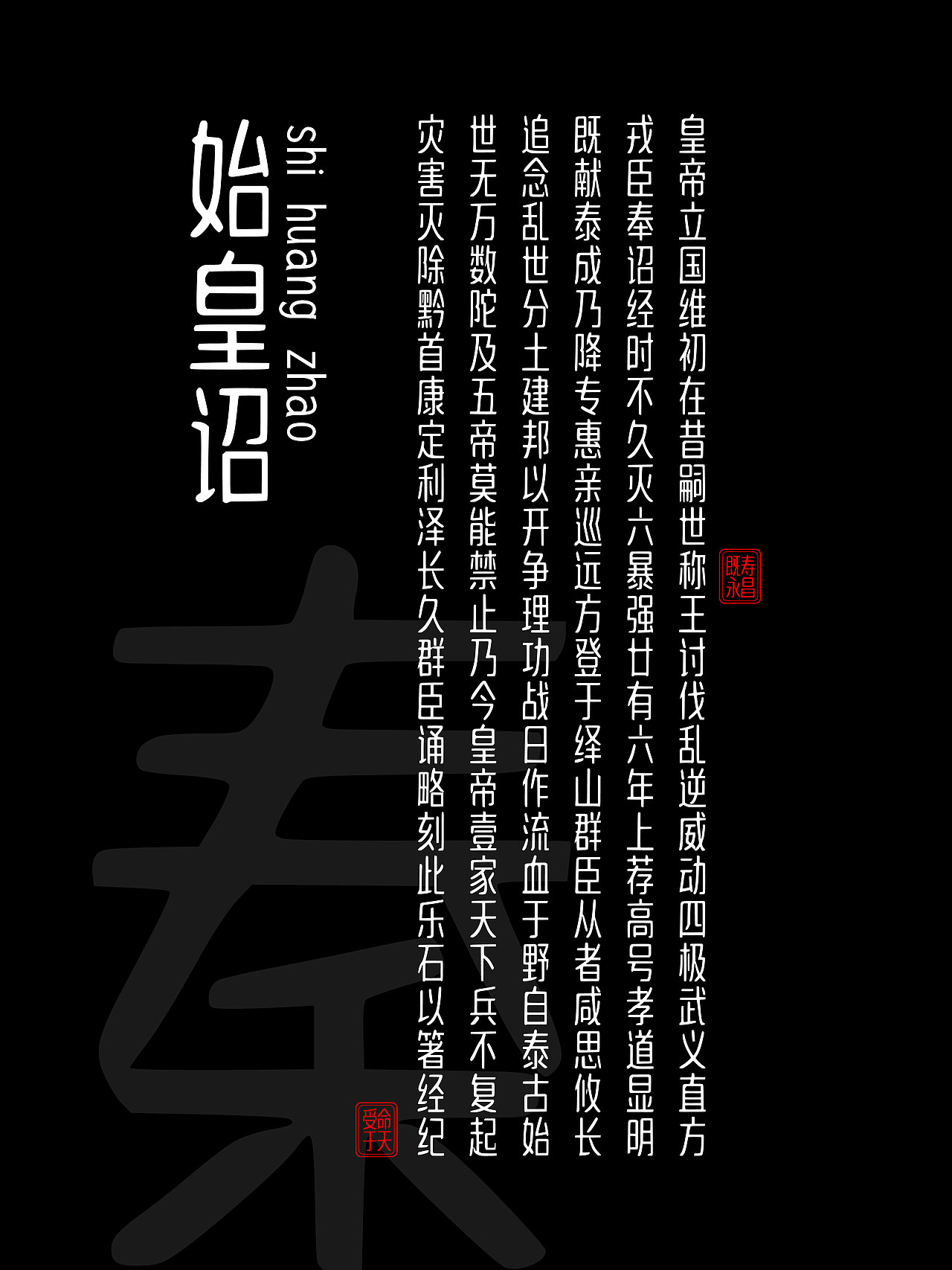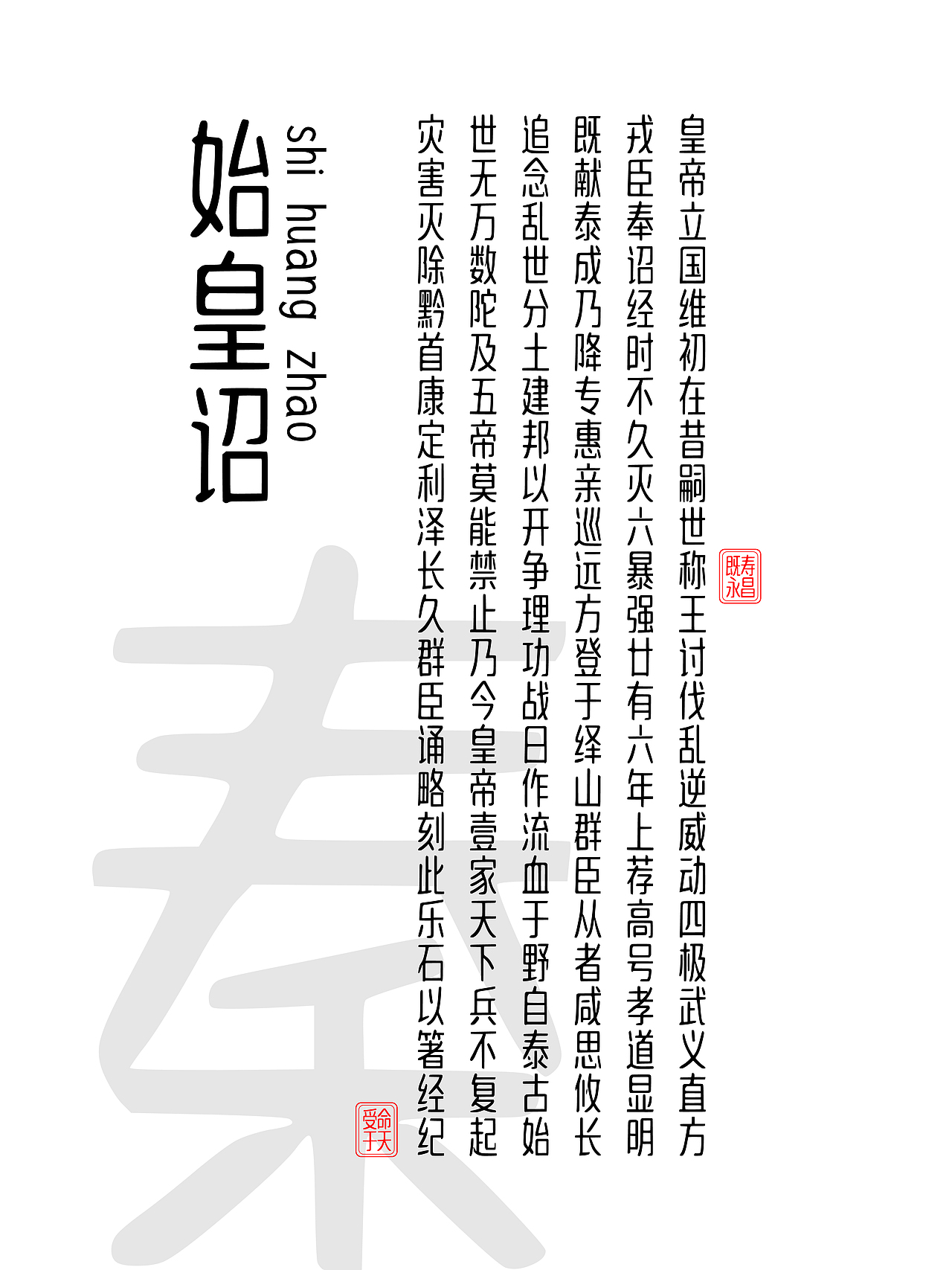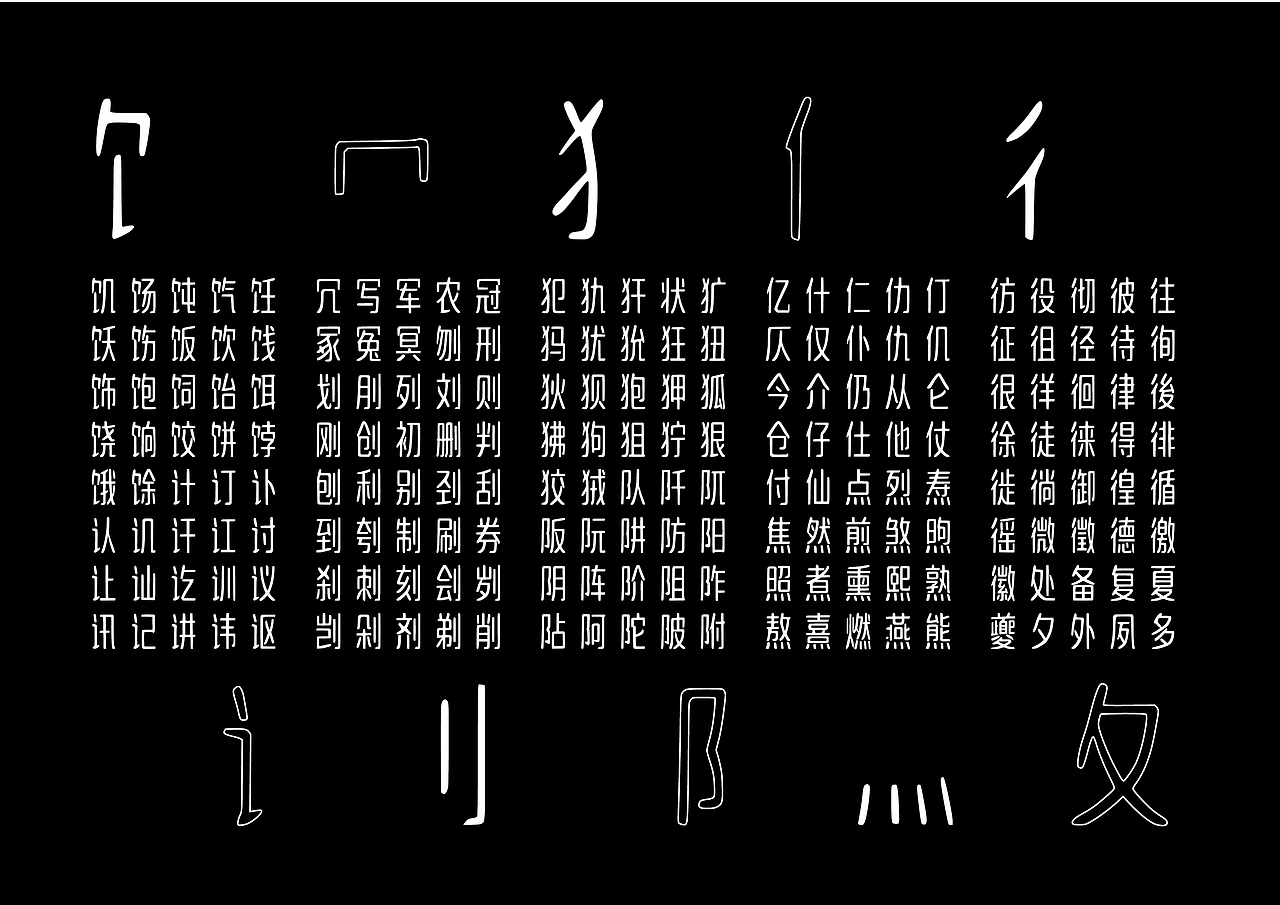
大萌秦 Da Meng Qin | 现代小篆字体
大萌秦字体确实是一种非常独特且富有创意的字体设计。它以秦朝的小篆为基础,融合了现代字型的元素,既保留了小篆的古典韵味,又符合现代人的阅读习惯,使得字体既易看又易懂。
秦朝的小篆,作为中国古代的一种重要书体,具有独特的艺术价值和历史意义。其字形端庄、线条流畅,富有节奏感,给人一种古朴典雅的感觉。然而,由于小篆的字形与现代常用字存在一定的差异,对于现代人来说,阅读起来可能会有些困难。
大萌秦字体正是在这样的背景下应运而生。它巧妙地结合了秦朝小篆和现代字型的优点,既保留了小篆的古典美,又使得字体更加易于阅读和识别。这种设计不仅让人们在欣赏字体美感的同时,也能轻松地理解文字所表达的意思。